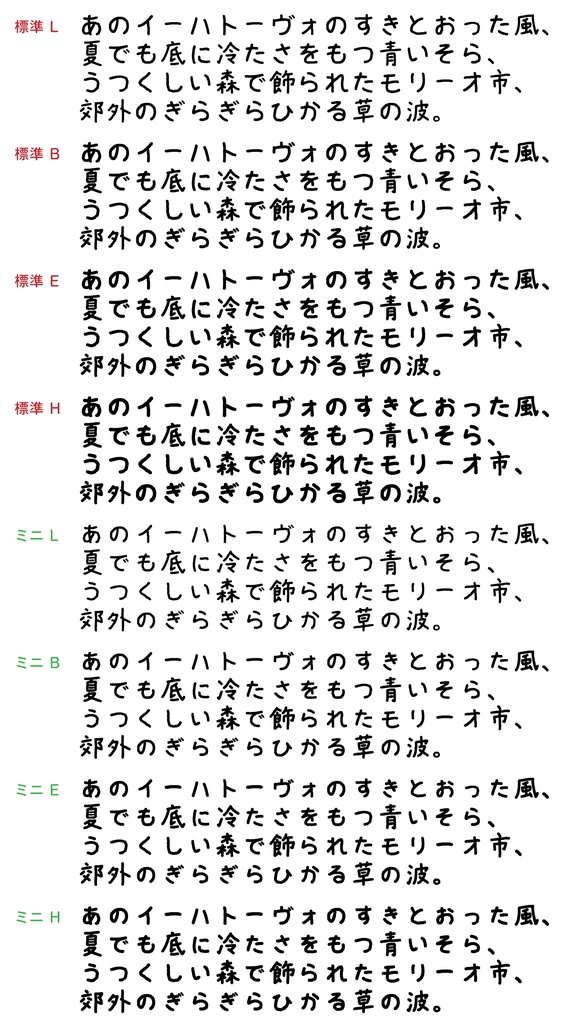
TK-takumiゆるりフォント L
TK-takumiゆるりフォントの「ウェイトL」です。 かな文字の大きい「標準」フォントとかな文字が小さめの「ミニ」フォント、それぞれのフォントに等幅フォントとプロポーショナルフォント(計4フォント)を同梱しております。 2019年5月からの新元号「令和」の合字も入力できます(U+32FFに収容)。
どんなフォント?
「takumiゆとりフォント」の反省点を踏まえて制作したフォントです。 takumiゆとりフォントは、以前よりユーザーの皆さんから「かわいい」「面白い」などの評価をいただいている一方で、「読みにくい」「クセが強い」というご意見もありました。そこでtakumiゆとりフォントの反省点を踏まえ、可読性を高くすることに注視して制作したフォントがこの「takumiゆるりフォント」です。 かな文字を大きめに、ふところを広くとり、ゆったり、ゆるりとしたイメージになるように設計し、かな文字ごとの黒み、濃さ、太さの違いができるだけ少なく見えるように作りました。やわらかく、かわいらしく、POPな印象を強調しつつも、読みやすさと真面目な手書きの印象を残しているので、幅広い用途でお使いいただけます。